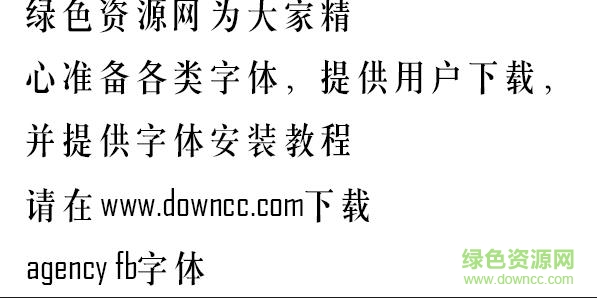
agency fb英文字體ttf中每一個字母如果是封閉的樣式將看到一個個四方形的圈,讓你感受到獨(dú)特的視覺享受,它的風(fēng)格十分有趣,很適合應(yīng)用到孩子所喜愛的場所或者書籍中,快來綠色資源網(wǎng)下載吧!
agency fb字體將帶給你獨(dú)特的英文字體樣式體驗(yàn),是一款能夠讓你立刻愛上它的優(yōu)質(zhì)字體,運(yùn)用范圍十分廣泛,受到萬千用戶喜愛!